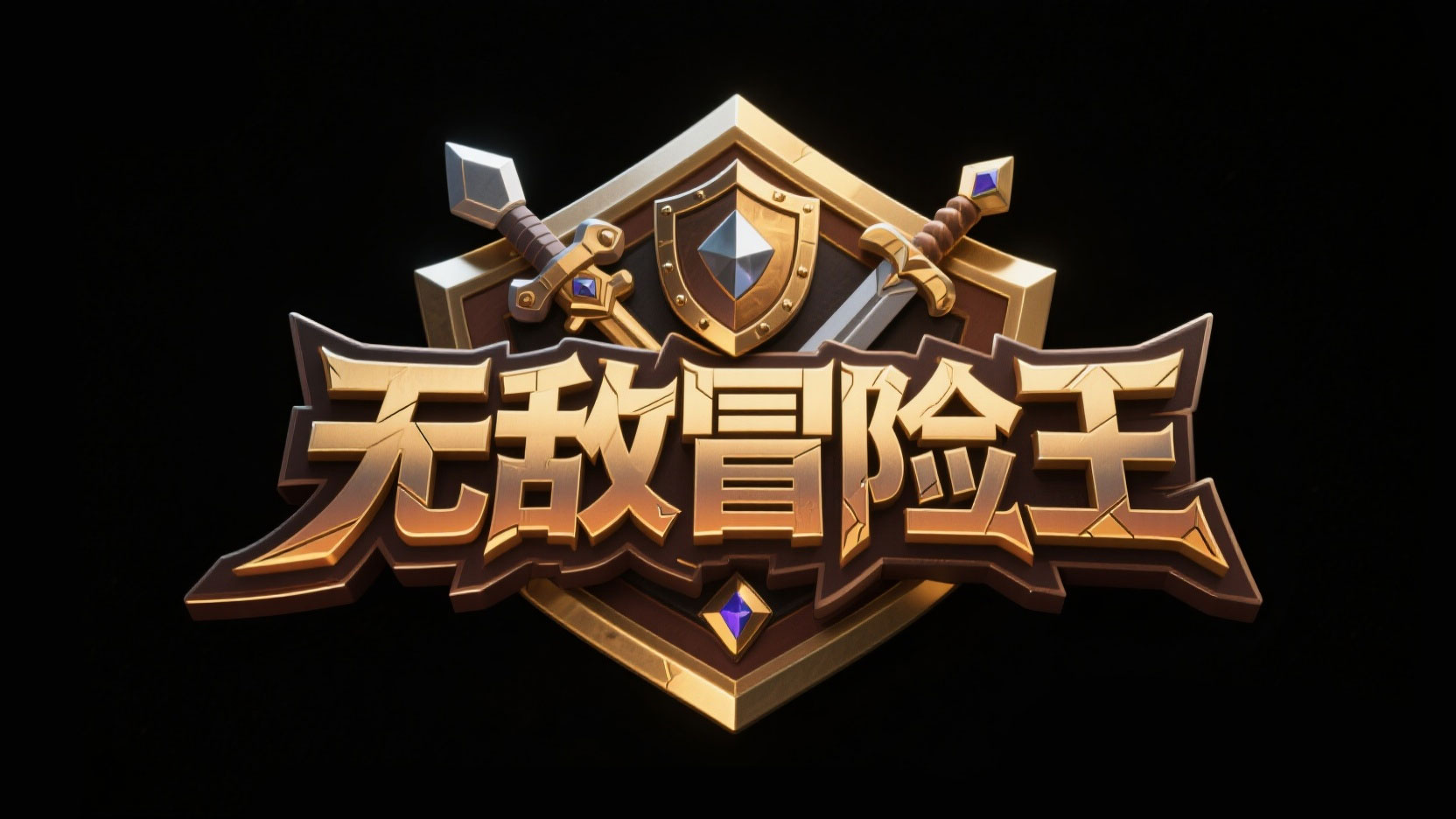
创作一个奇幻冒险金属徽章风艺术字“无敌冒险王”...
创作一个奇幻冒险金属徽章风艺术字“无敌冒险王”...AI字体提示词
游戏标题完整提示词可直接复制
风格定位
适合做风格探索与字形灵感延展。
适合场景
海报设计、品牌标题、电商设计、创意视觉
创作一个奇幻冒险金属徽章风艺术字“无敌冒险王”,汉字融入冒险符号(武器、盾牌、宝石 ),模拟冒险徽章形态;金棕渐变填充 + 深色描边,笔画添加金属纹理、高光切割;多层深色阴影 + 亮色高光层叠。背景为干净的黑色。
可替换关键词
金属纸张肌理浮雕高对比立体阴影强笔触盾牌宝石)+
生成建议
• 先保留核心风格词,再替换材质、颜色和光影词做多轮尝试。
• 如果用于品牌标题字,补充品牌气质、行业属性和情绪关键词。
• 如果用于海报或电商标题,额外强调大字、对比度和视觉冲击力。